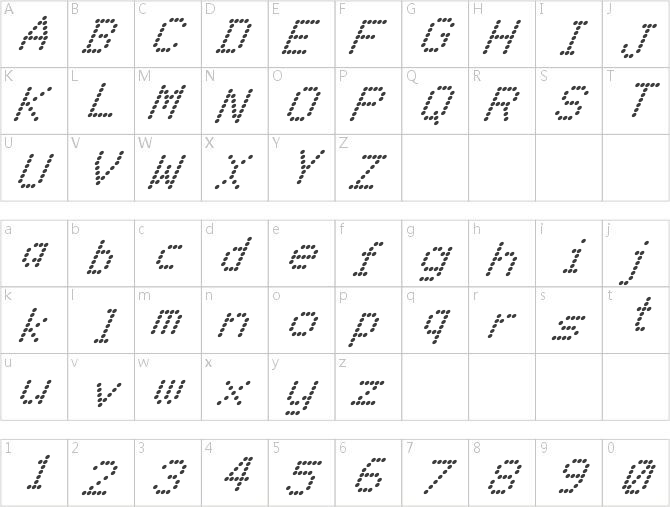
FZ DIGITAL 9 ITALIC 詳情頁(yè)
FZ DIGITAL 9 ITALIC字體字庫(kù)是一款讓人賞心悅目、百看不厭的英文字體,適合各類廣告和產(chǎn)品包裝設(shè)計(jì)應(yīng)用,字體大小0.09MB,格式為ttf字體,上傳用戶是1733150348,作者/版權(quán)方為未知